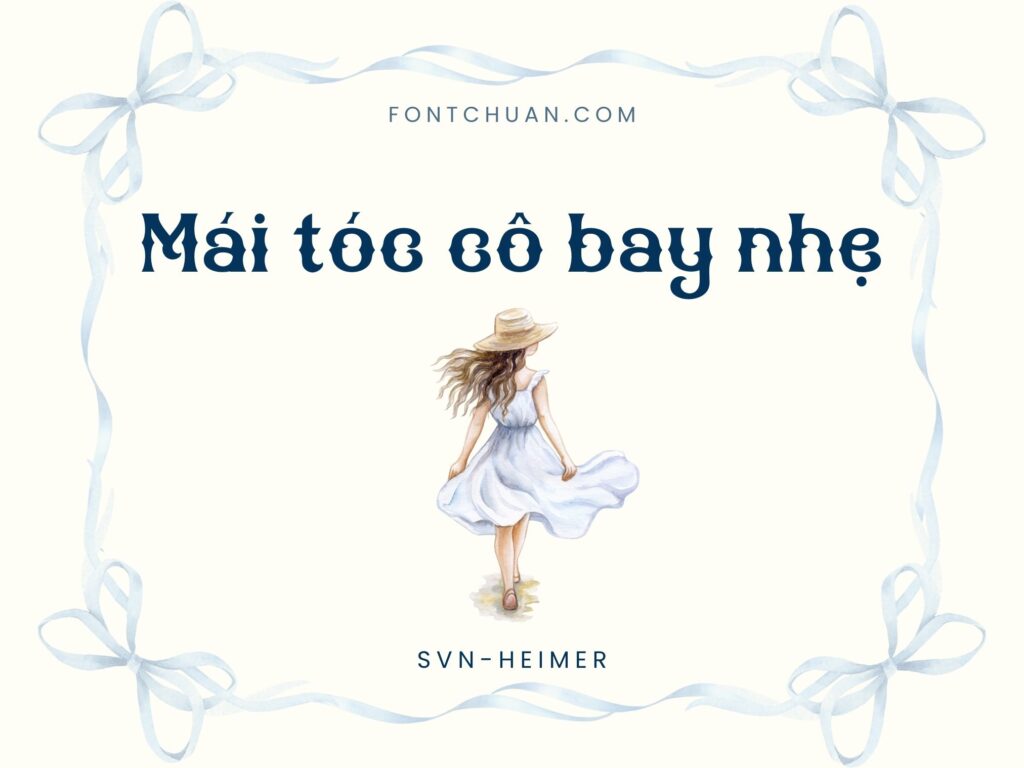
Font SVN Heimer Việt Hóa
Tác giả Font: Runsell Type Designer
Heimer là một kiểu chữ serif cổ điển được thiết kế bởi Runsell và phát hành trên Envato Elements, mang theo phong cách thanh lịch và sang trọng đặc trưng. Phiên bản Việt hóa được thực hiện bởi Styleno.1 Fonts giúp font này hỗ trợ tiếng Việt hoàn chỉnh và hơn 100 ngôn ngữ khác trên toàn cầu. Font đã được thành viên Font Chuẩn chọn lọc, sưu tầm và giới thiệu nhằm phục vụ cộng đồng thiết kế trong việc tìm kiếm những kiểu chữ chất lượng cao cho các dự án thực tế.
Các ký tự trong Heimer có chân chữ dứt khoát, độ dày vừa phải, bố cục cân đối và tính nhất quán cao giữa các glyph. Sự cổ điển trong thiết kế kết hợp với nét hiện đại khiến font này trở nên lý tưởng cho các ấn phẩm in ấn cao cấp, tiêu đề tạp chí, bao bì sản phẩm hoặc thiết kế nhận diện thương hiệu. Heimer đặc biệt phù hợp với các lĩnh vực như quảng cáo, bất động sản, spa và giáo dục nhờ khả năng truyền tải thông điệp một cách trang trọng và tin cậy.